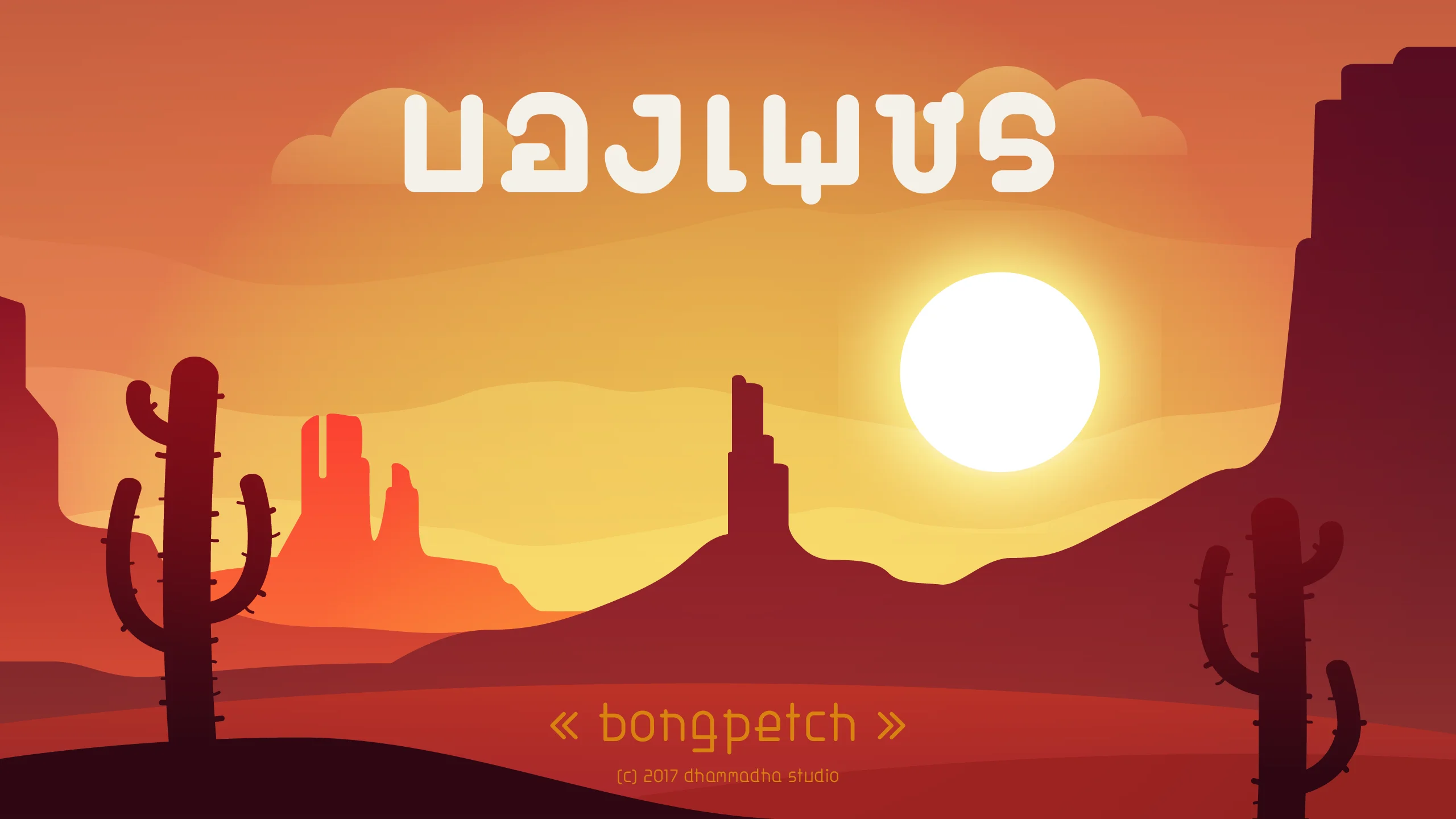
bongpetch
ชุดอักษรที่ได้รับแรงบันดาลใจจากโครงสร้างและรูปร่างอันโดดเด่นของต้นกระบองเพชร โดยหยิบยกเอกลักษณ์ของการเชื่อมต่อเส้นในลักษณะคล้ายการลากเส้นต่อจุดมาสร้างสรรค์เป็นตัวอักษร เราได้ทำการลดทอนรายละเอียดให้ดูสะอาดตาและทันสมัยยิ่งขึ้น แต่ยังคงไว้ซึ่งกลิ่นอายของที่มาอันน่าสนใจ สะท้อนผ่านชื่อ 'บองเพชร' ที่บ่งบอกถึงตัวตนของฟอนต์ชุดนี้ได้อย่างเป็นเอกลักษณ์ ให้ความรู้สึกที่ดูโปร่งสบาย สม่ำเสมอ และมีความขี้เล่นแฝงอยู่อย่างลงตัว ด้วยรูปทรงที่เน้นความเรียบง่ายแต่มีจังหวะการจัดวางที่ดูแปลกใหม่ บองเพชร จึงเหมาะอย่างยิ่งสำหรับงานออกแบบที่ต้องการความทันสมัยและดูเป็นมิตร ไม่ว่าจะเป็นงานสร้างแบรนด์ที่เน้นไลฟ์สไตล์ การออกแบบกราฟิกสำหรับสื่อดิจิทัล หรือการใช้เป็นตัวอักษรพาดหัวในงานที่ต้องการความโดดเด่นในสไตล์มินิมอล ฟอนต์ชุดนี้จะช่วยให้งานออกแบบของคุณดูมีรายละเอียดที่น่าค้นหาและสื่อสารความสร้างสรรค์ออกมาได้อย่างชัดเจน